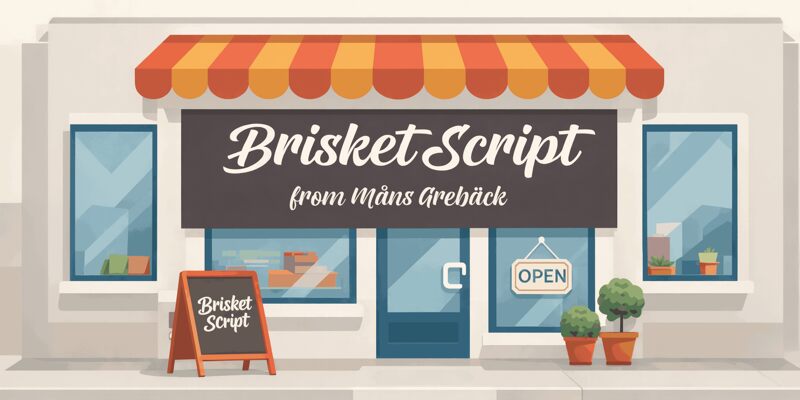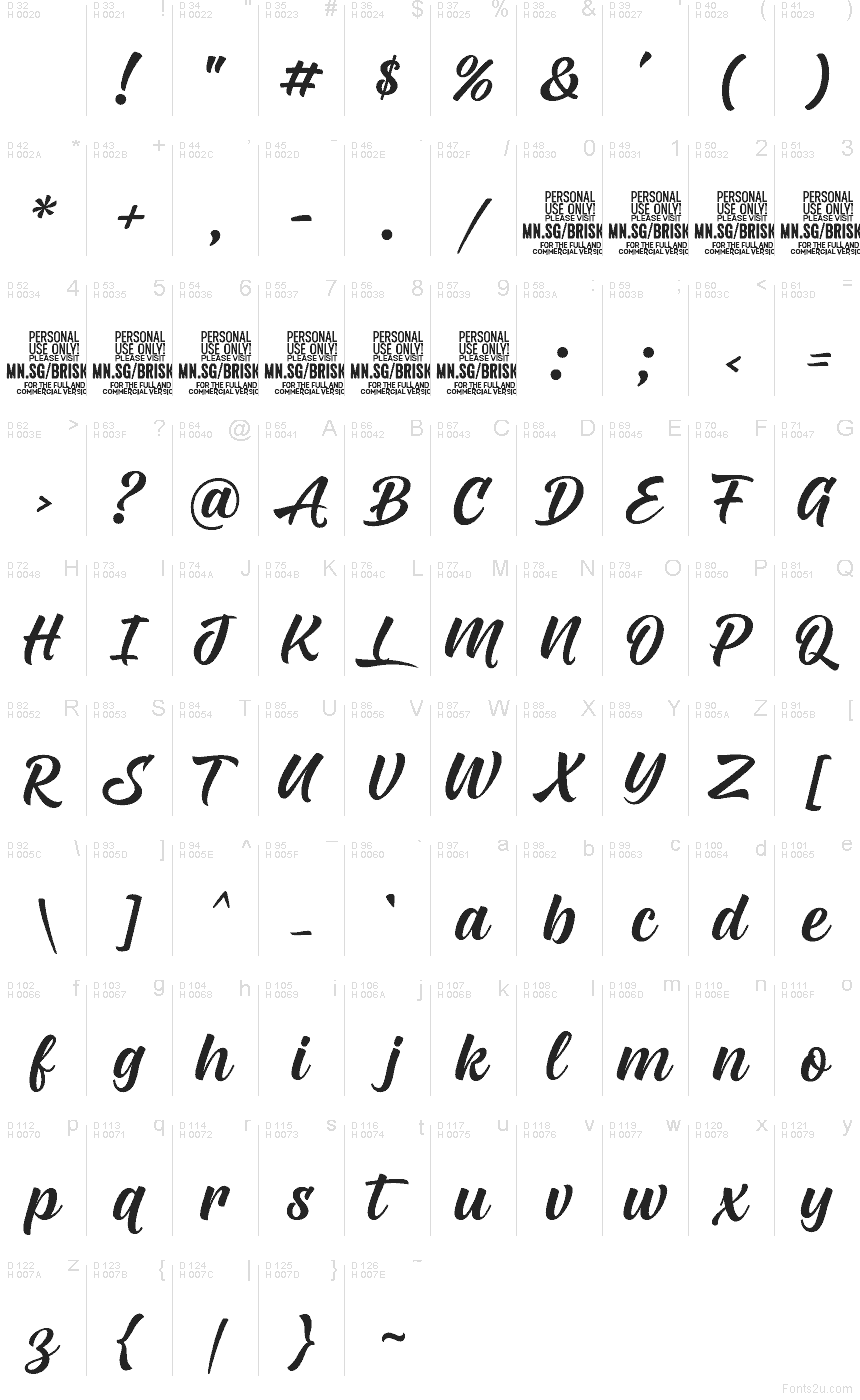
Brisket Script PERSONAL USE Regular
Brisket Script di Mans Greback AB è un font brush script gratuito con lo slancio audace delle insegne dipinte a mano e un aspetto rapido e calligrafico. Le lettere presentano tratti larghi e affusolati con giunzioni arrotondate; le ampie asole iniziali e le finiture fluide conferiscono al font un aspetto vivace, deciso e leggermente retro.
È perfetto per il food branding, menu di bar, etichette, titoli di poster e packaging in cui si cerca un font gratuito che sembri fatto a mano piuttosto che disegnato con precisione meccanica. Usalo per titoli brevi, loghi o copertine: i suoi attacchi ampi e le terminazioni nette a pennello conferiscono grande dinamismo anche a poche parole.